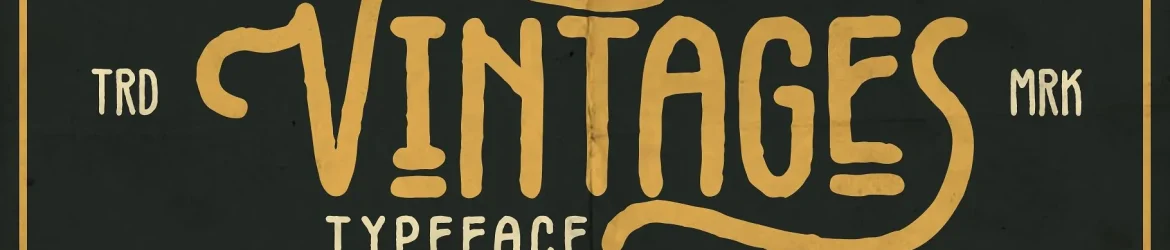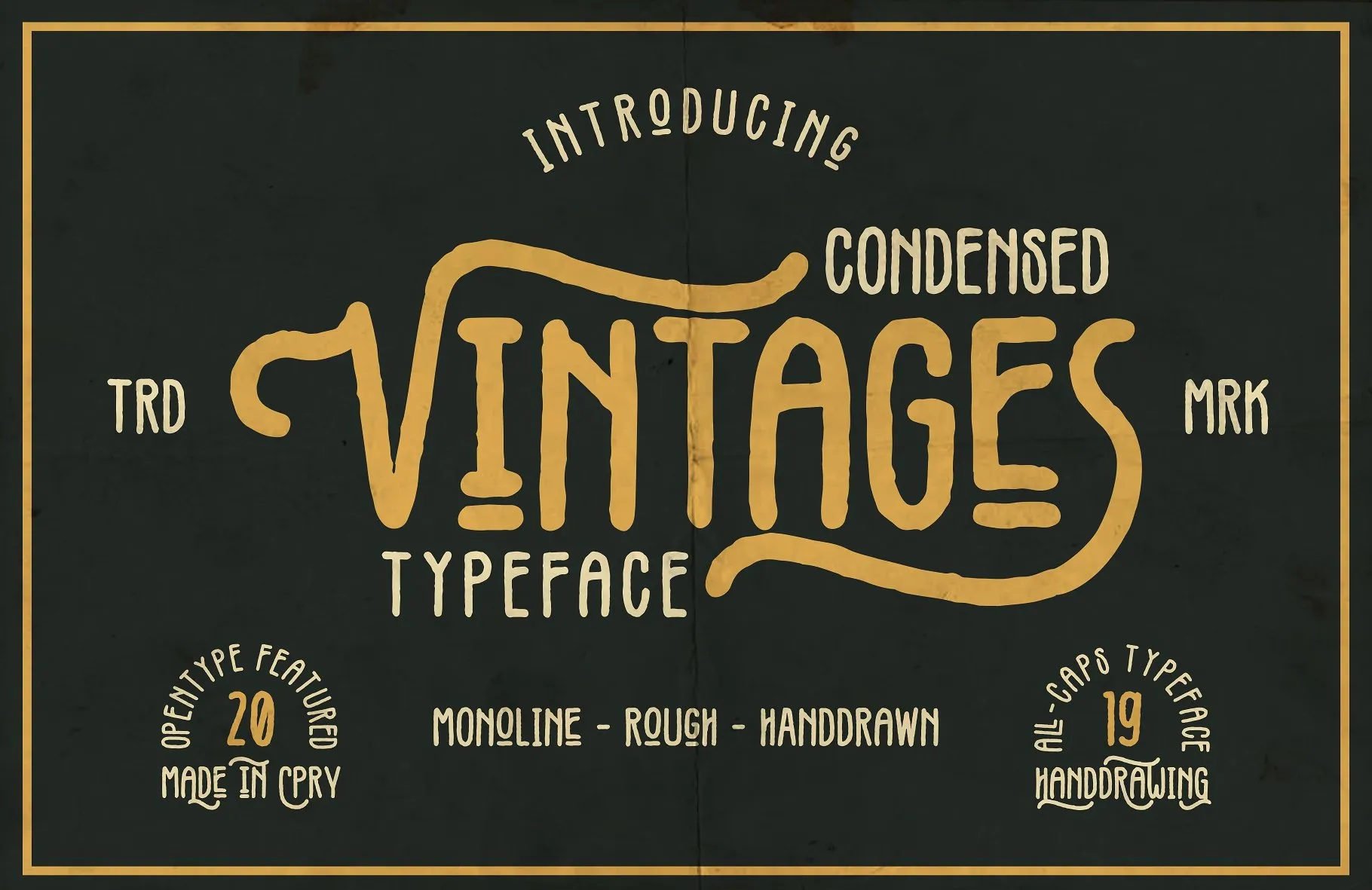
Vintages Typeface – Fonte Grátis
Vintages Typeface
A Vintages Typeface é uma fonte display moderna com um toque vintage retrô, criada por Garisman Std. Esta fonte monocromática e compacta se destaca como uma opção versátil para vários projetos, desde logos e letras à mão livre até rótulos e postais. Com todas as letras em maiúsculas, combina o charme de tipografia clássica com um estilo desenhado a mão moderno. É perfeita tanto para quem deseja uma linguagem minimalista e elegante quanto para os que valorizam estilos vintage atemporais. Suas características condensadas permitem maior legibilidade em aplicações digitais, enquanto sua aparência vibrante e criativa destaca-se no mundo da design gráfico moderno. Sem dúvida, a Vintages Typeface é uma escolha perfeita para quem busca um equilíbrio entre o clássico e o contemporâneo, adaptado à moda atual do design de fontes display.